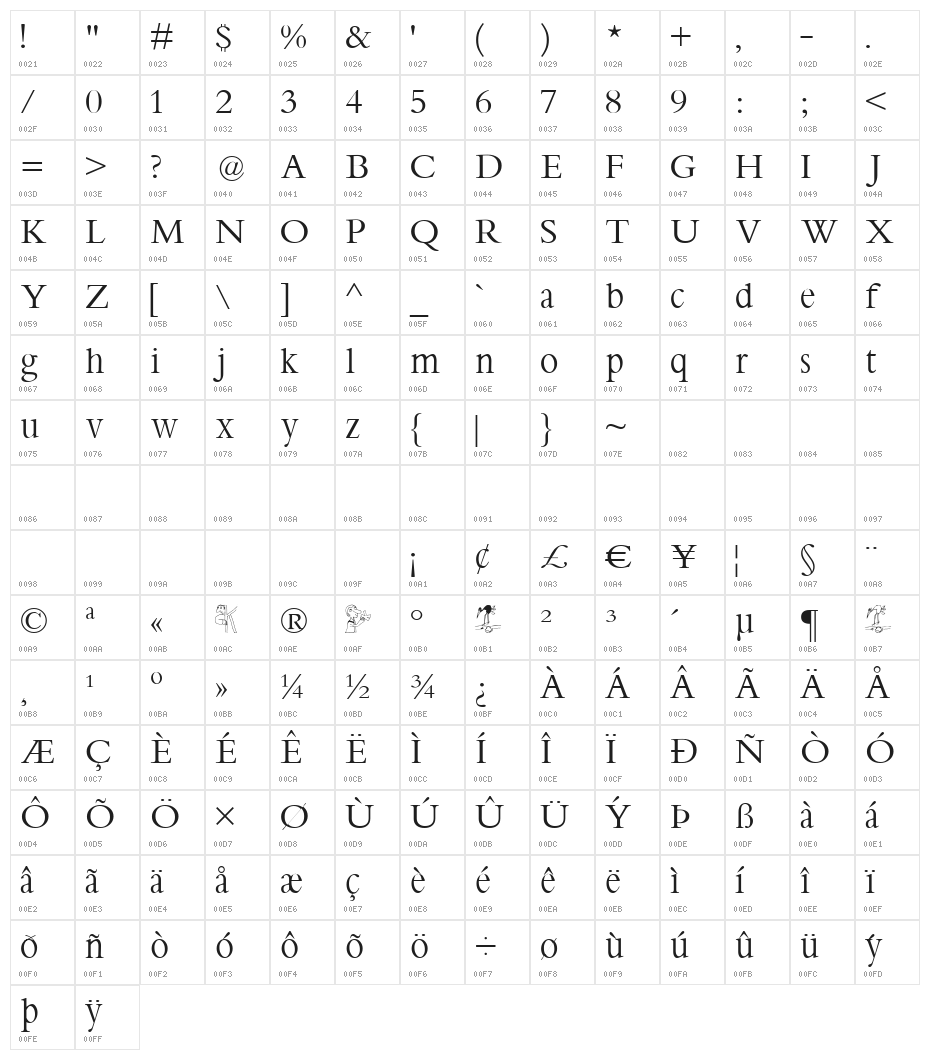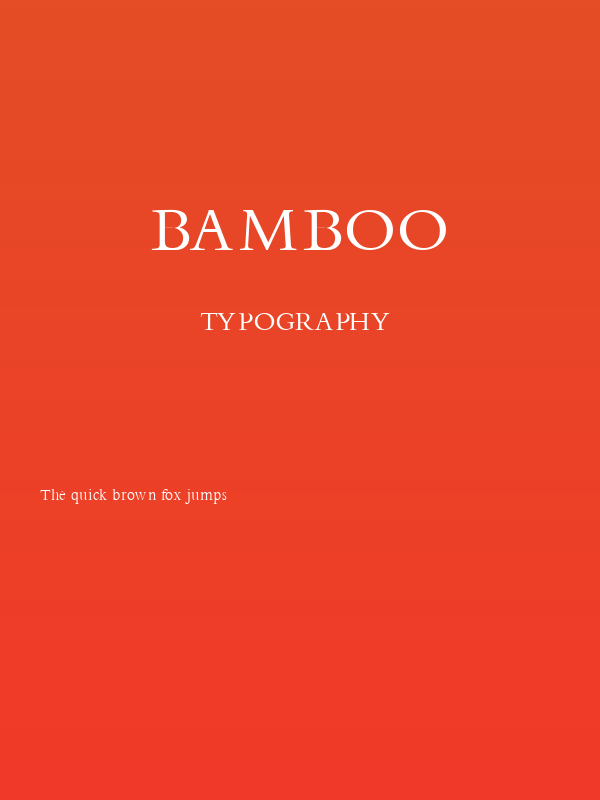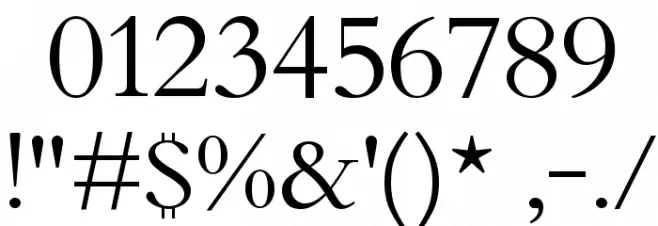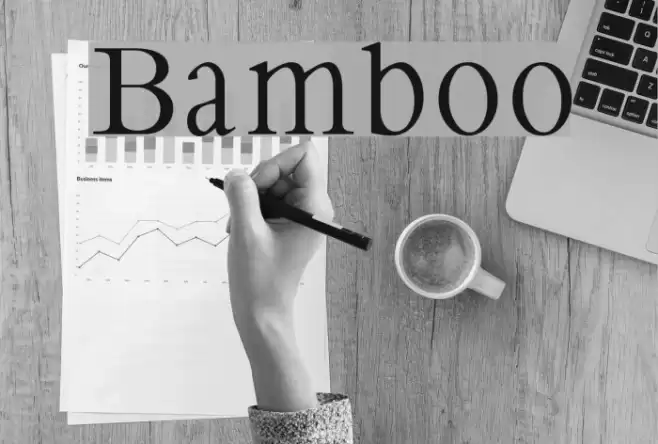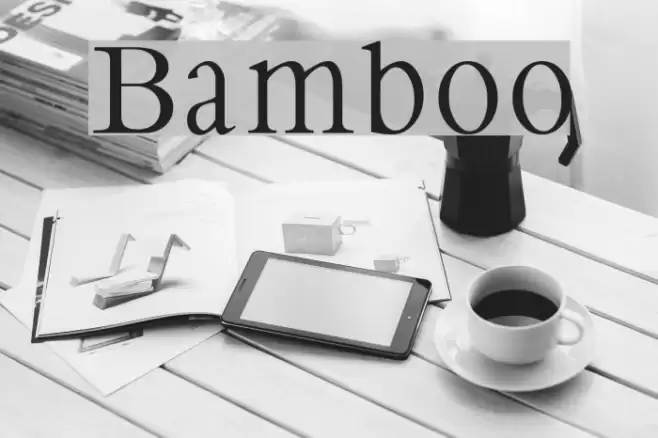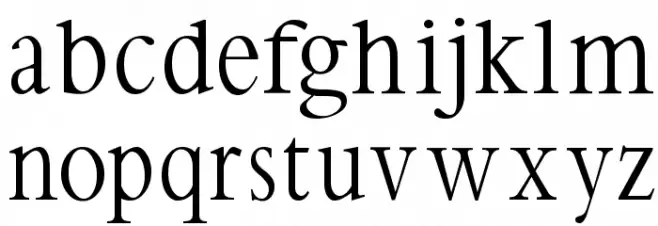
Bamboo Font
| Progetti proposti | Ideal for editorial design, book covers, formal invitations, and branding projects that require a touch of elegance and tradition. |